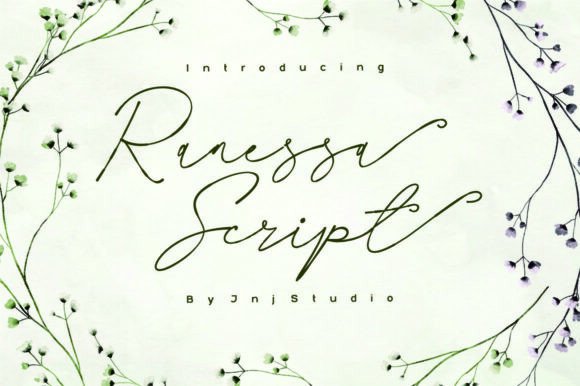
Ranessa Script
Cho dù bạn đang tạo sản phẩm POD (In theo yêu cầu), thiệp mời đám cưới hay đồ họa mạng xã hội, Ranessa Script đều là một sự lựa chọn lý tưởng.